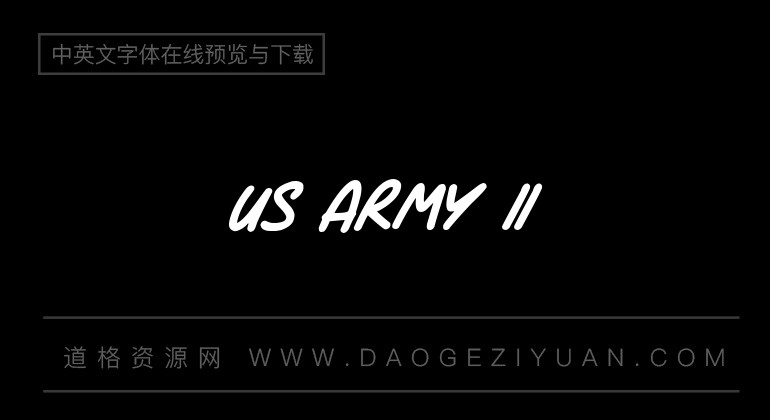
US Army II 字体是由美国陆军于 2020 年发布的一种新字体。这个字体是为了取代之前被广泛使用的另一种字体 “Standard” 而设计的。 US Army II 字体采用了现代化的设计风格,它的特点是字形简洁,线条粗细均匀,易于辨认。这种字体被设计成适用于各种不同的应用场景,包括印刷品、数字媒体、标志等。 US Army II 字体的设计灵感来源于美国陆军的传统价值观和现代形象。它的字形和排版都经过了精心的设计和测试,以确保其最大程度地符合军方的需求和要求。 总的来说,US Army II 字体是一种非常现代化的字体,它既具有美国陆军传统的特点,又符合现代设计的需求。它的使用范围广泛,可以为美国陆军的各种应用场景提供高质量的排版和印刷效果。内容介绍
US Army II是一款非常不错的手写艺术字体,具有很好的视觉感,适合于文化类的宣传设计、商业类品牌的广告和产品包装设计以及个性化文字排版等较多场景。